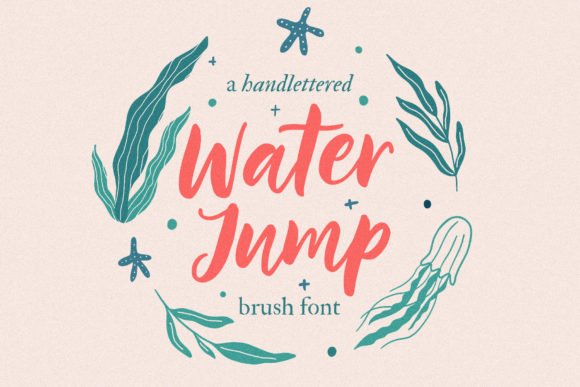
Water Jump - это шикарный и матовый шрифт.
Стильные чередования и лигатуры делают этот шрифт идеальным для любого проекта.
Смело добавляйте его в свои любимые творения и позвольте себе поразиться полученному результату.